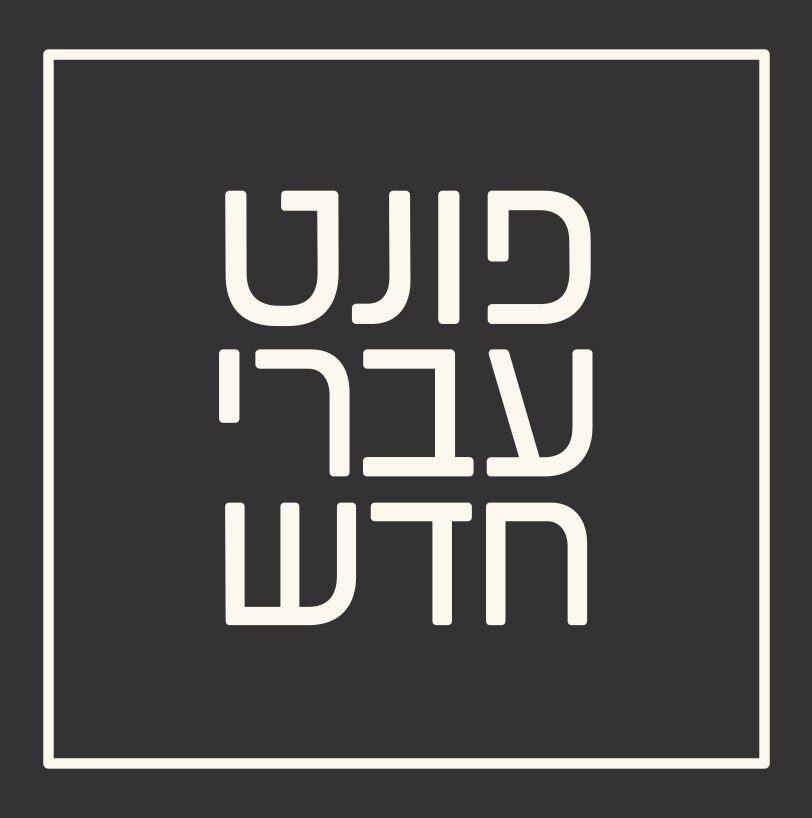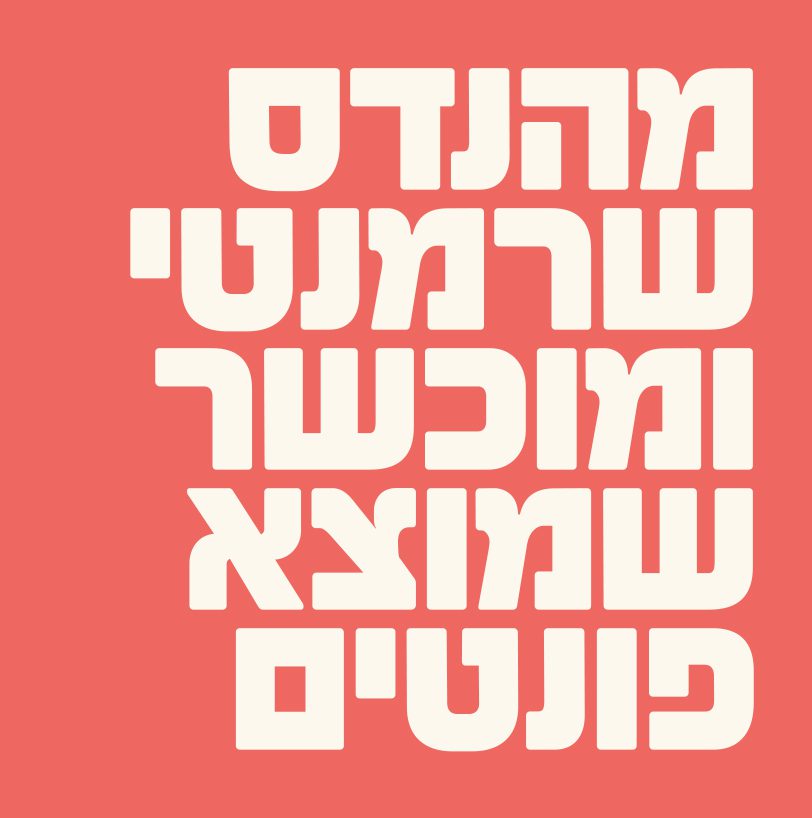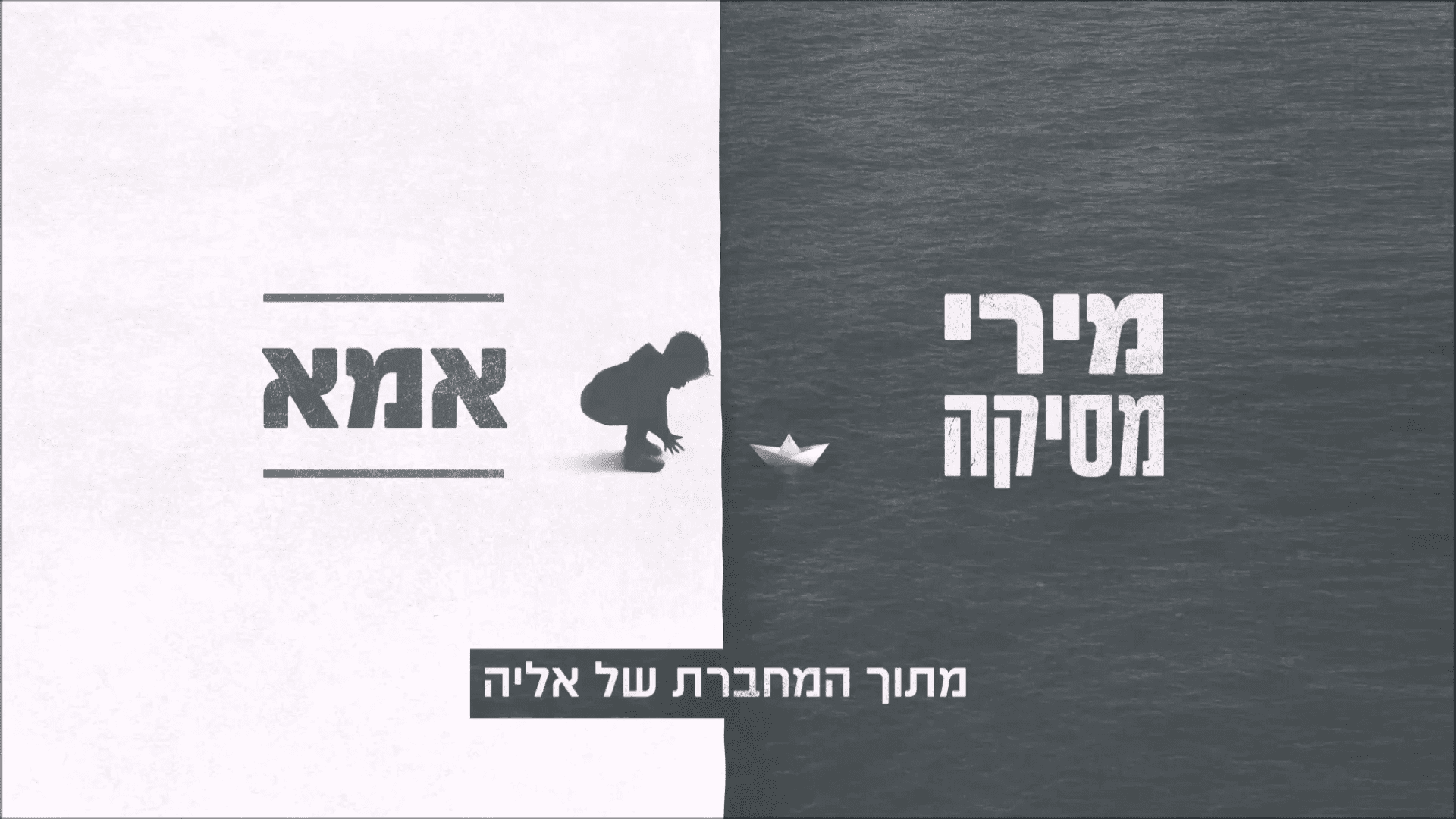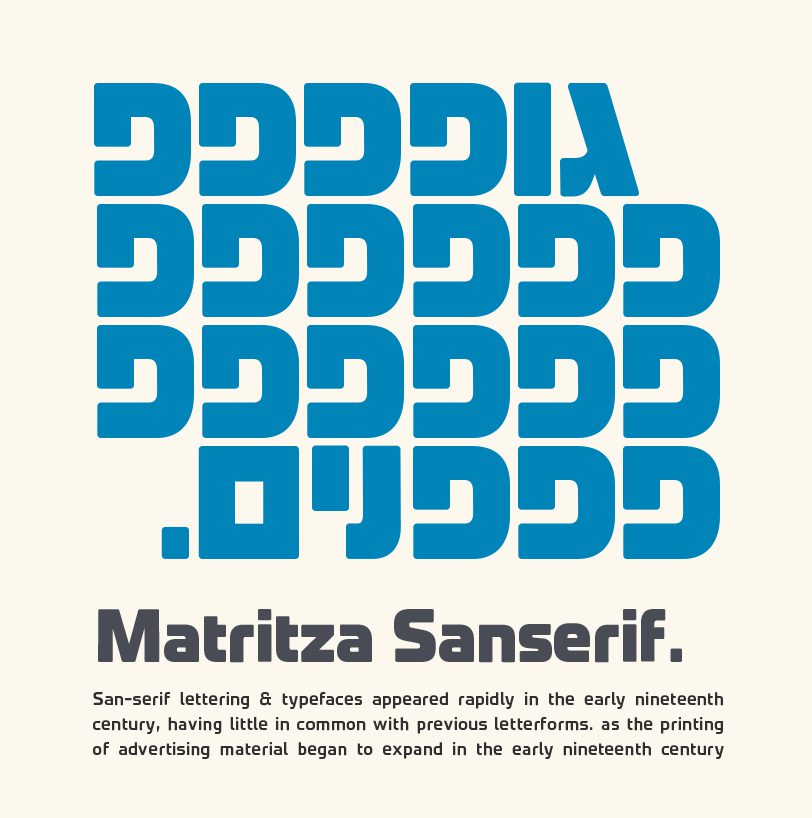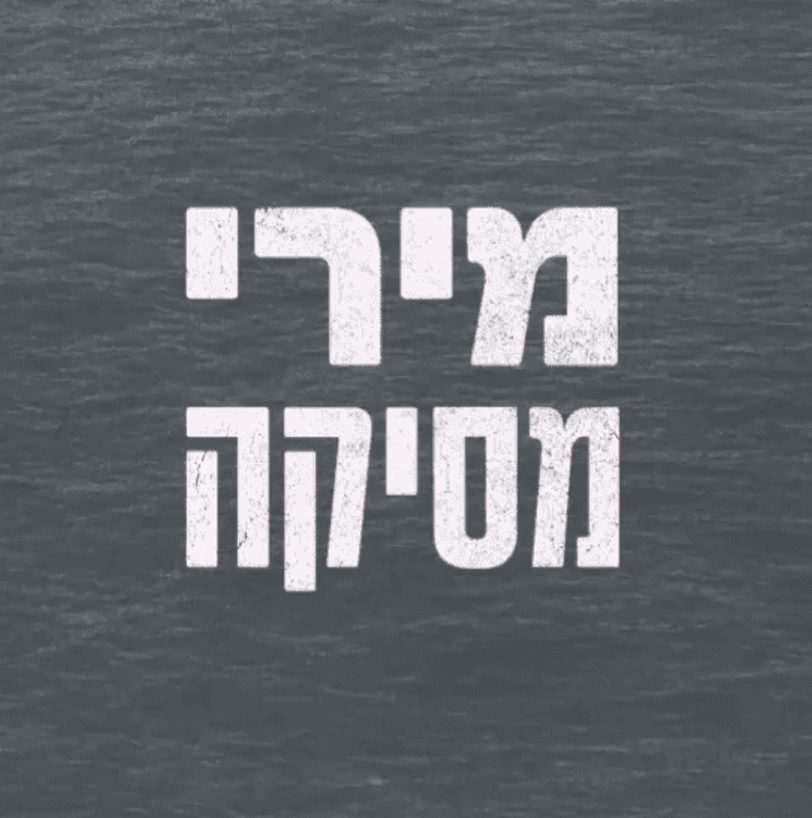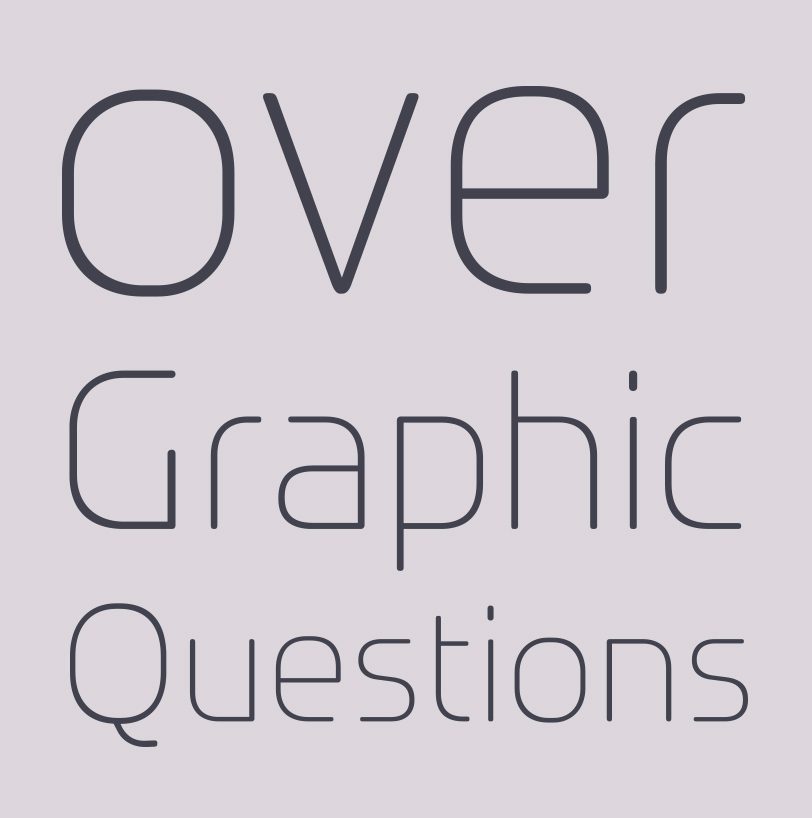
מטריצה
מטריצה / Fb Matritsa
• שם הגופן:מטריצה
• מעצב הגופן:נדב עזרא
• סגנון:סאן סריף
• מאפיינים: דקיק קל רגיל בינוני כבד שחור
• תכונות: אוונגרדי אלגנטי מודרני מעוגל מרובע פשוט קוסמטי
סיפור הגופן:
גופן מטריצה קיבל את שמו מפני שנבנה על גריד גאומטרי הדוק וחסר פשרות, כאילו נלקח מעולם המדע המדויק. מאופיין בשפה צורנית פשוטה עם קריצות ייחודיות ובשמבנה יציב עם קצוות עגולים, מה שמאפשר לגופן שימוש ורסטילי ומראה ייחודי בו- זמנית. גופן זה קיים בעברית ובכל השפות הלטיניות ומתפרש למשפחה מרובת משקלים כולל גרסא צרה על מנת לאפשר למעצב בו טווח נאה של שימושים.